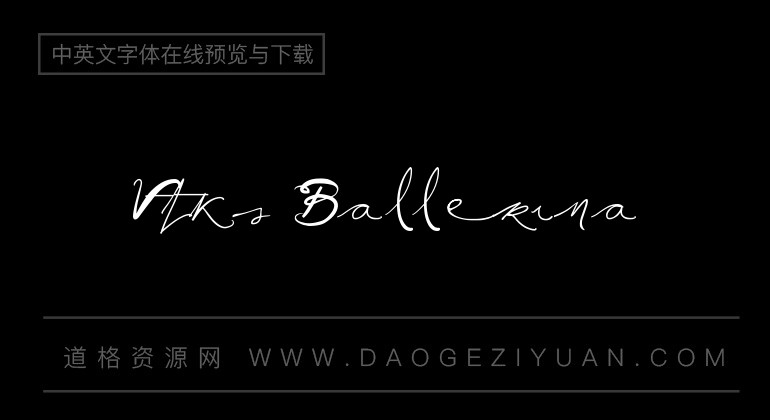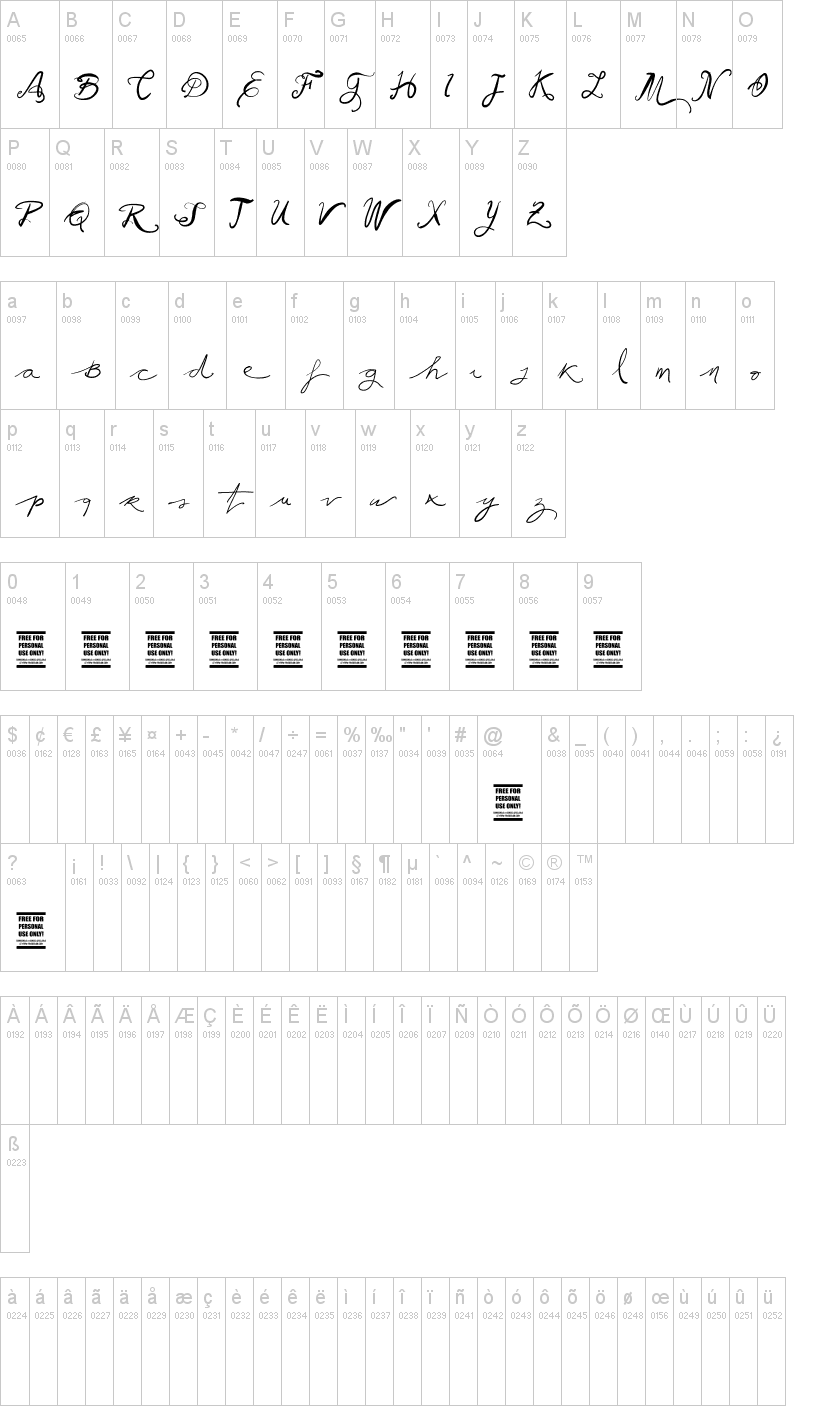
Vtks Ballerina 是一款手写风格的英文字体,由著名设计师Vitorio Takaoka所创作。它具有温柔、细腻、优雅的特点,适合用于招牌、海报、书籍封面等设计。它的字形曲线流畅,每个字母都有其独特的线条,可以带给读者一种柔和的感觉。此外,它还有很多变体,可以满足不同的设计需求。内容介绍
Vtks Ballerina是一款非常不错的手写艺术字体,具有很好的视觉感,适合于文化类的宣传设计、商业类品牌的广告和产品包装设计以及个性化文字排版等较多场景。